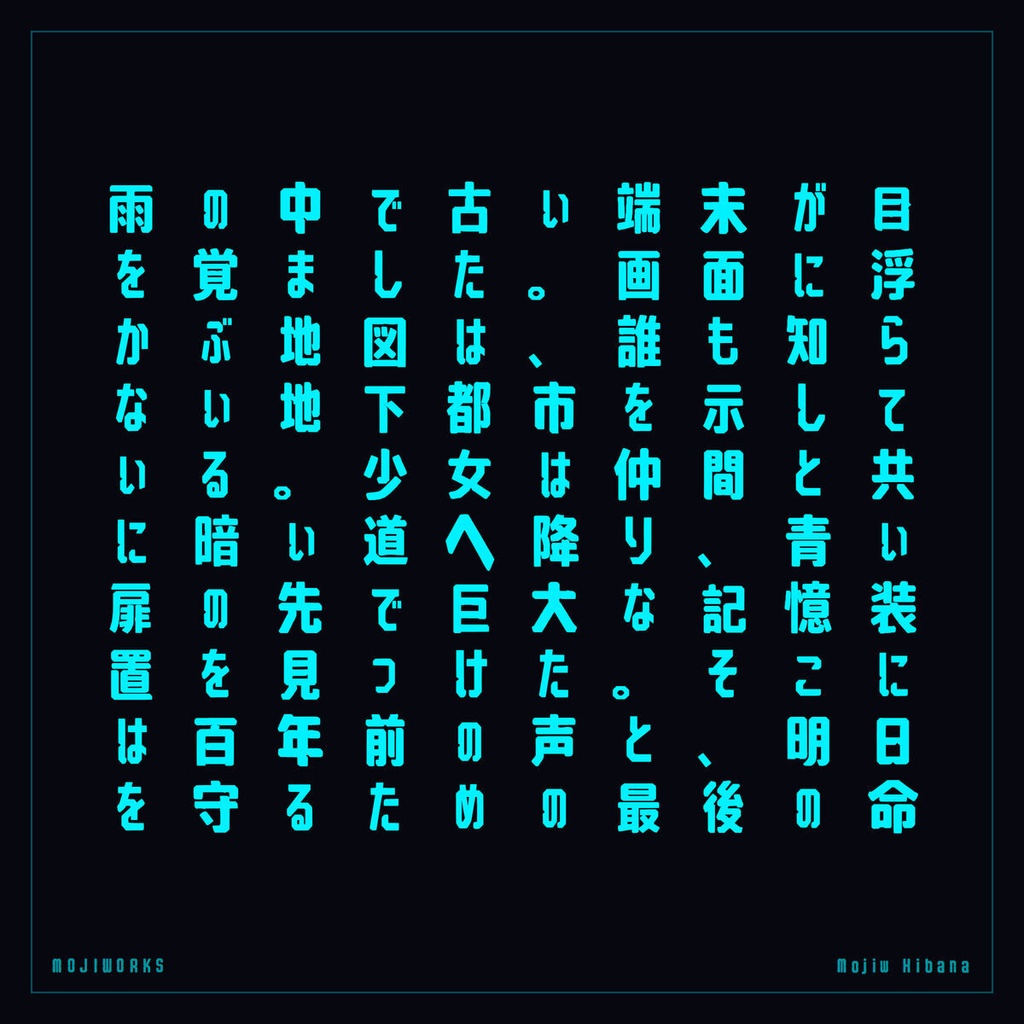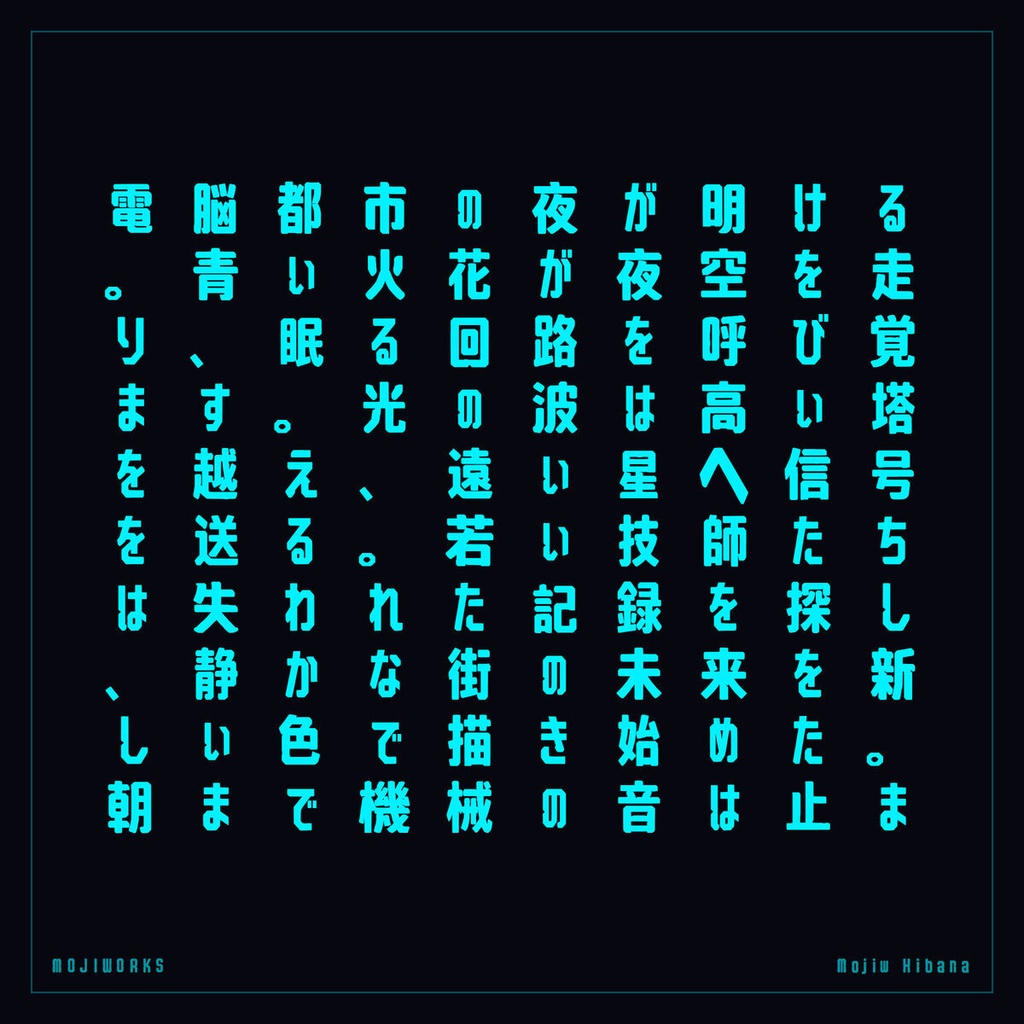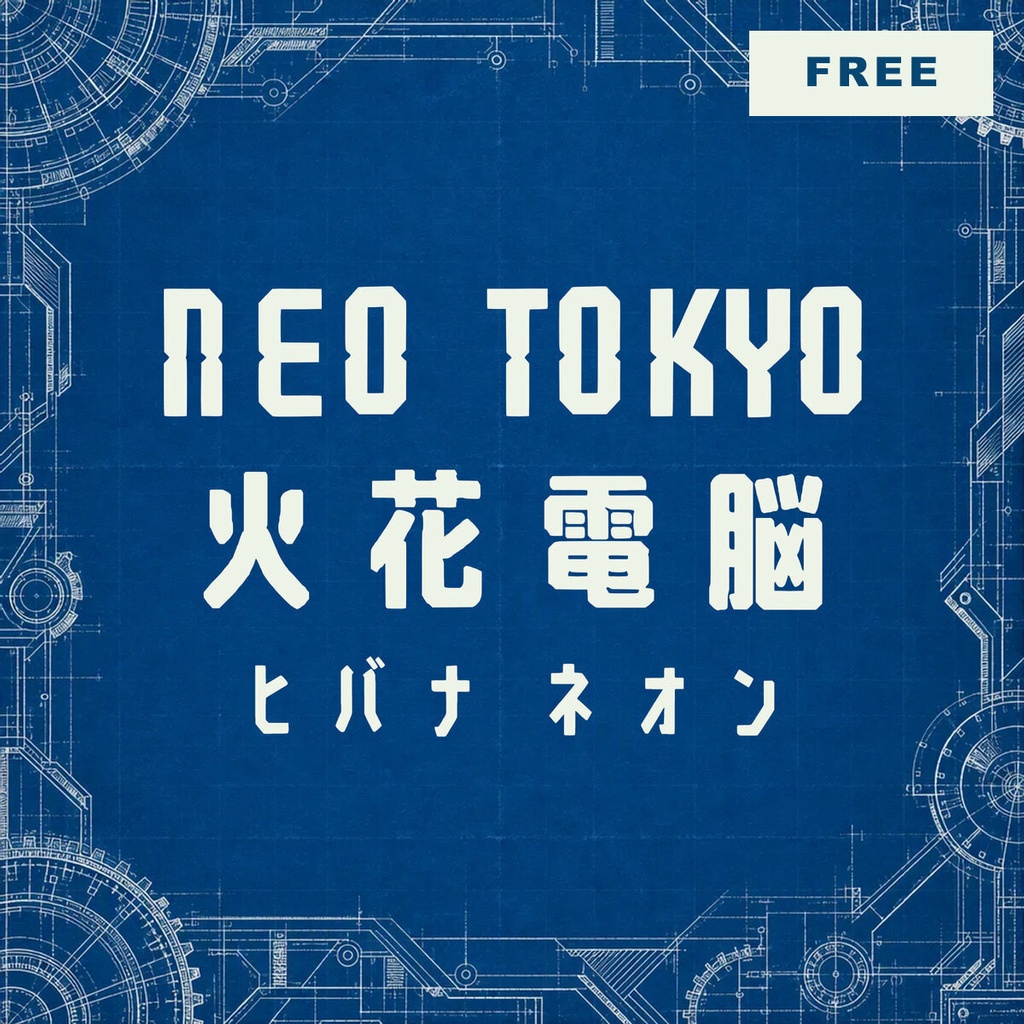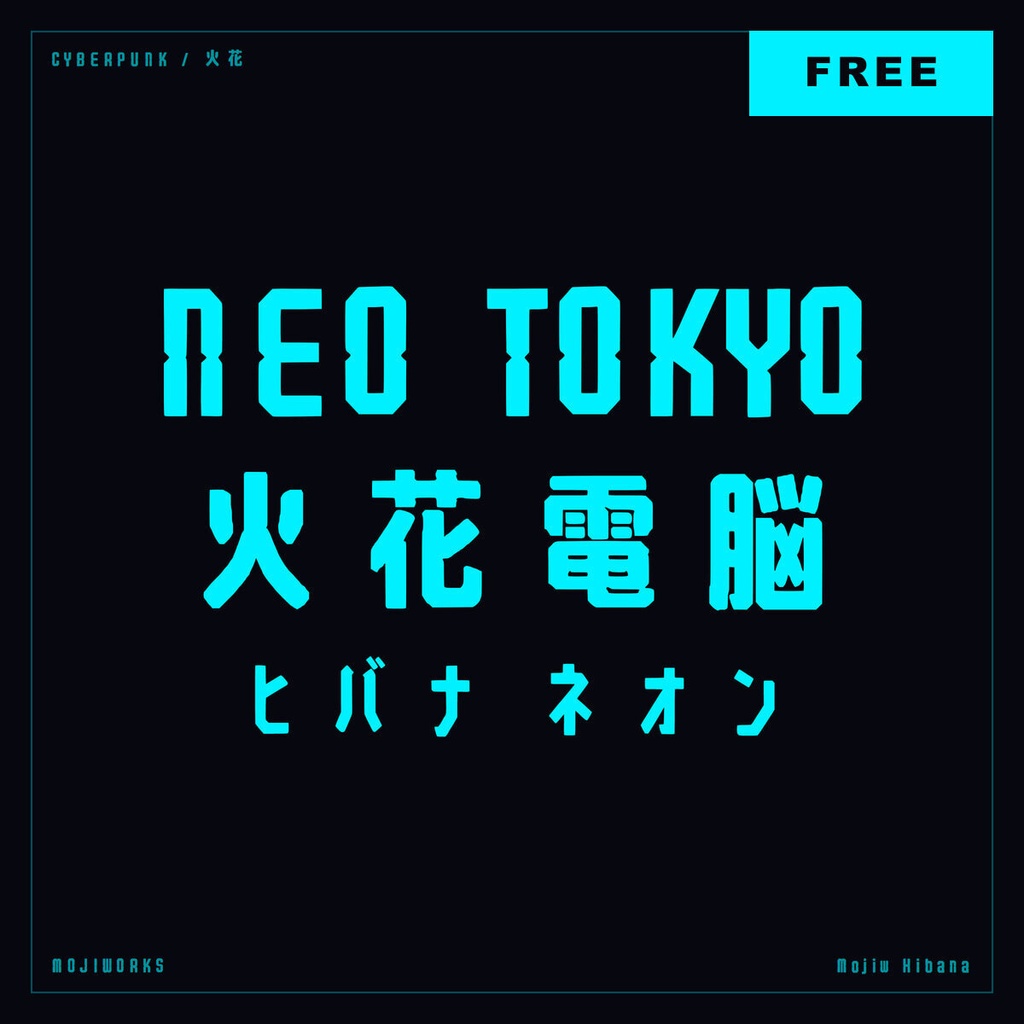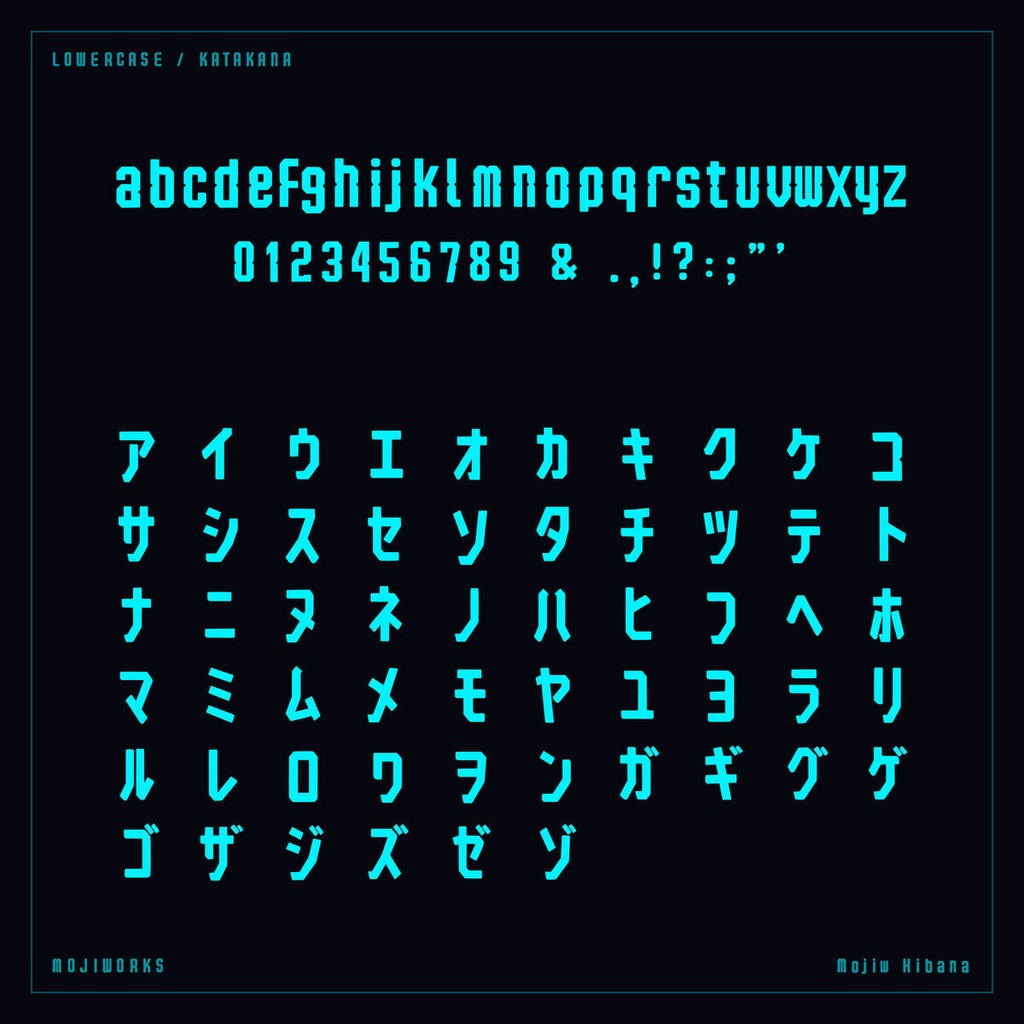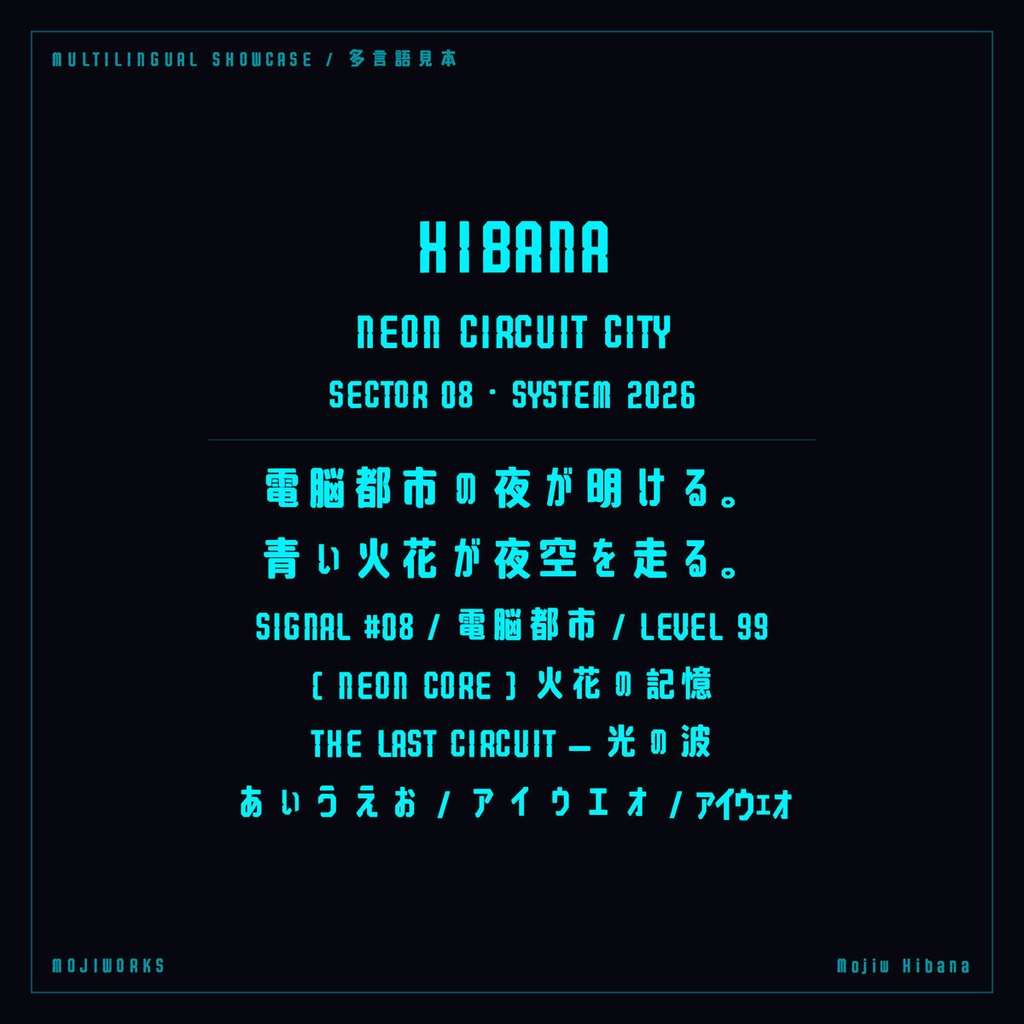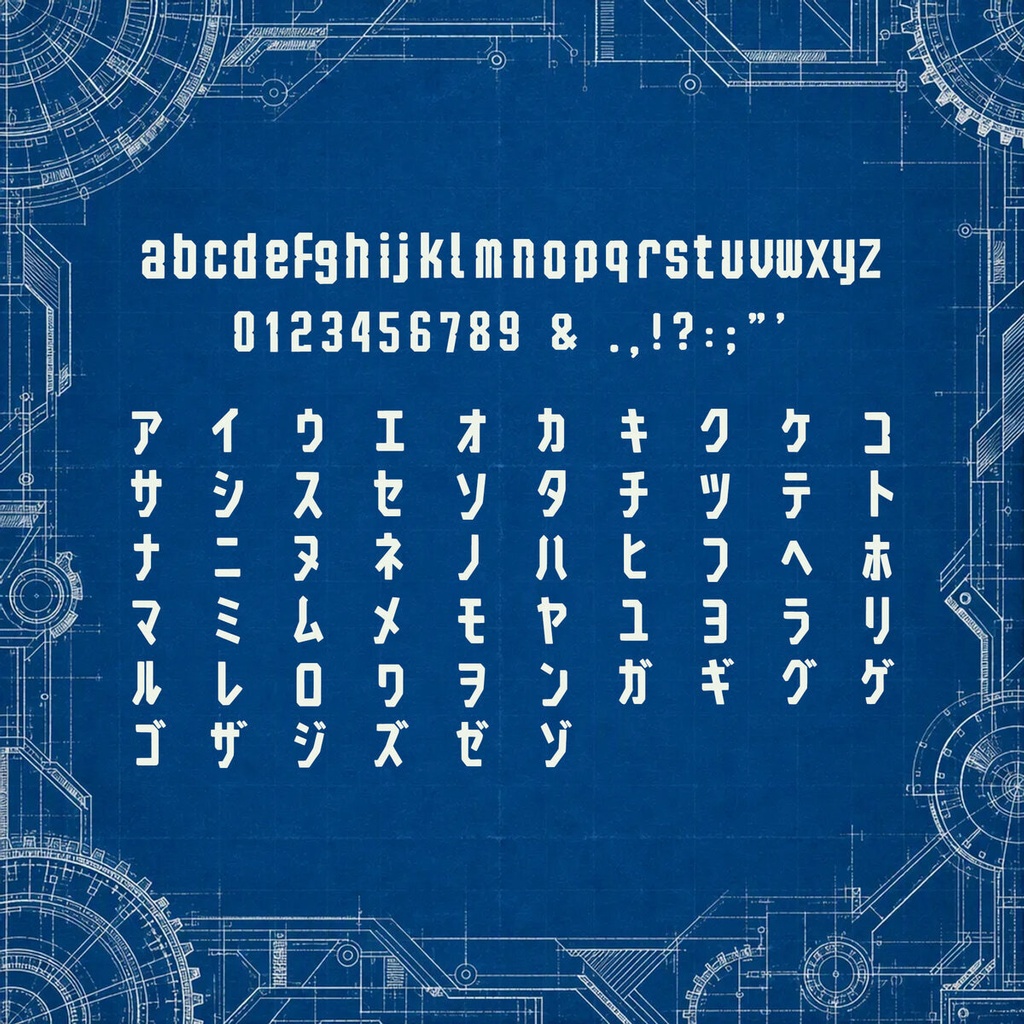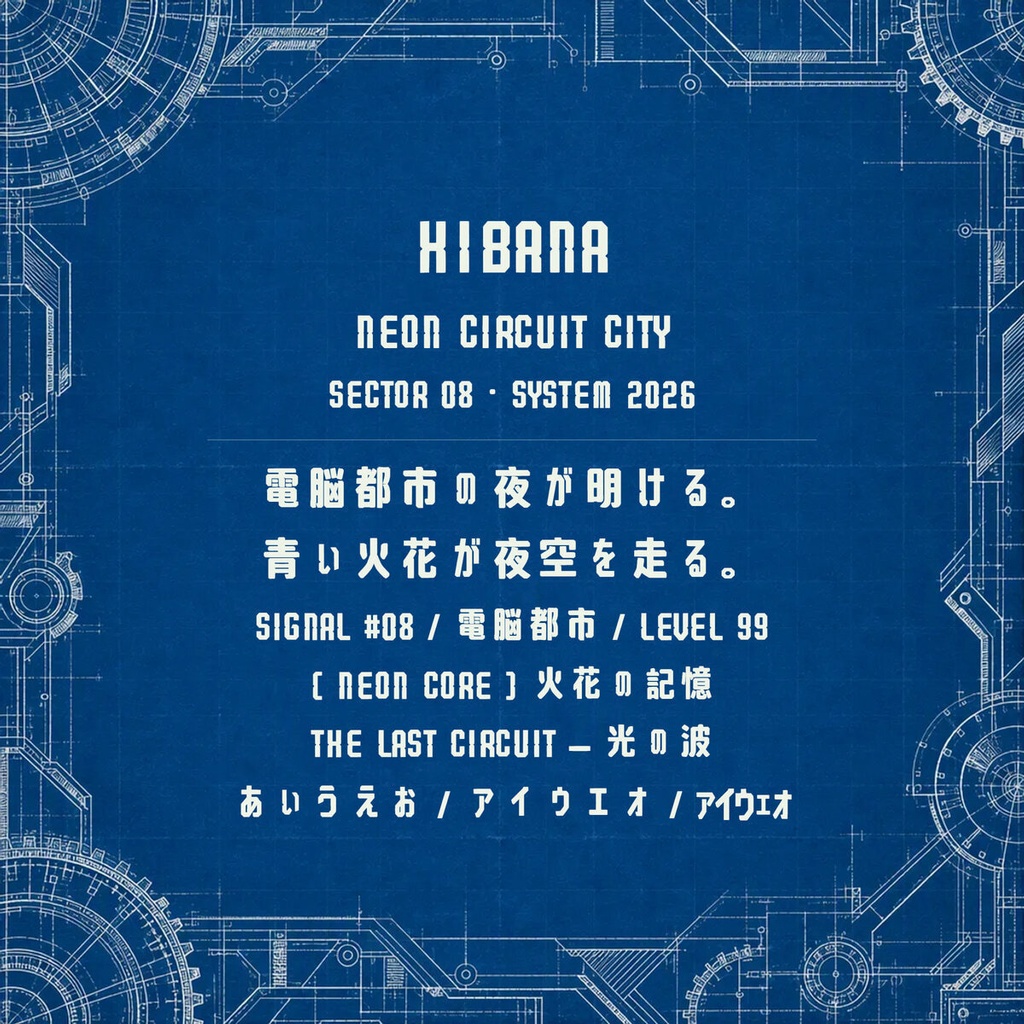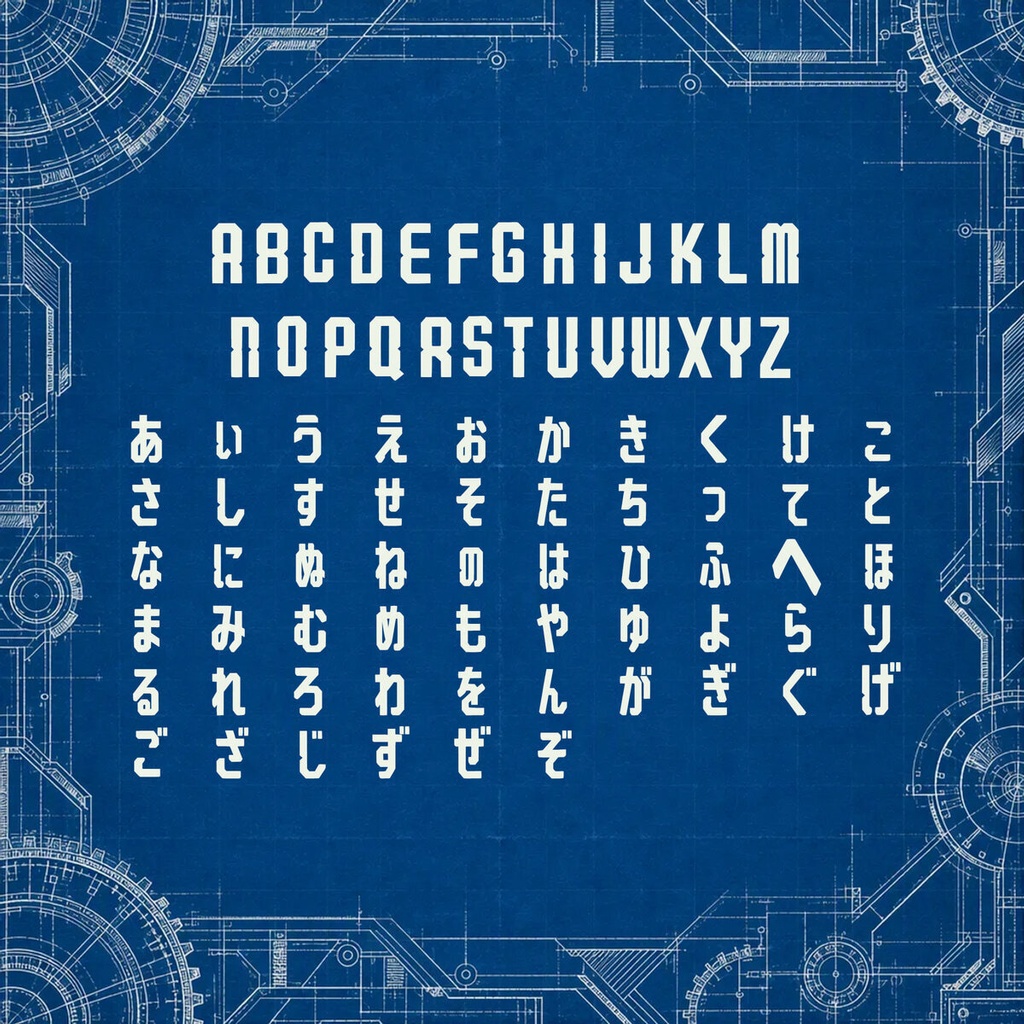
火花 Hibana Standard【フォント】|かな・英数字301文字
ネオンが弾ける、サイバーパンクなディスプレイ書体です。 A cyberpunk display face cut with electric neon energy. 【用途 / Use】 SF / サイバーパンク / 配信OP / EDM MV / ゲームUI For science fiction, cyberpunk, stream openings, EDM videos, and game UI. 【スタンダード版 / Standard】 ラテン文字・ひらがな・カタカナ・記号を全301文字収録しています。漢字・半角カナは収録していません。 Includes 301 characters covering Latin, hiragana, katakana, and punctuation. Kanji and half-width kana are not included. 301文字 / characters 【関連する収録版 / Other Edition】 常用漢字2,136字を含む常用漢字フル版もあります。 The Joyo Complete edition also includes all 2,136 Joyo kanji. ▶ 常用漢字フル版 / Joyo Complete: https://mojiworks.booth.pm/items/8394466 【フォント仕様 / Specification】 バージョン / Version: 1.0.1 形式 / Format: TrueType (.ttf), Web (.woff2) 対応環境 / Platform: Windows, macOS, web browsers 収録字一覧 / Character list: CHARSET.txt 同梱 / Included: font files, README, LICENSE, character list, portfolio PDF, product previews. 【利用規約 / License Summary】 個人・商用利用可。1ライセンスは購入者1名に適用されます。 Personal and commercial use is permitted. One license covers one purchaser. 印刷・動画・ロゴ・グッズ等の静的成果物、および購入者が運営するサイトでの同梱WOFF2の利用が可能です。 Static output such as print, video, logos, and merchandise is permitted. The bundled WOFF2 may be used on a website owned or operated by the purchaser. ゲーム・アプリへの組み込みは、利用者が生のフォントを抽出できない形式に限ります。生のフォントを同梱する場合は別途ライセンスをご相談ください。 Game/app embedding requires protection against extraction of the raw font. Contact us for a separate runtime-embedding license when shipping raw font files. 標準ライセンスは1製品・1サイトあたり年間約100,000ユーザーまで。従業員50名超の組織を含む大規模利用は要相談。 Standard coverage is approximately 100,000 users per product/site/year. Larger use and organizations with more than 50 employees require an extended license. フォント本体の再配布・販売・貸与・変換・グリフ抽出・派生フォント制作・生成AI学習やスタイル参照は禁止です。 Redistribution, resale, lending, conversion, glyph extraction, derivative fonts, and generative-AI training or style reference are prohibited. 完全な利用条件は同梱の LICENSE.txt / LICENSE.jp.txt をご確認ください。 The bundled license files are authoritative; consult them for the complete terms. 【ほかのフォント・カスタム制作 / More Fonts and Custom Work】 フォント一覧、オーダーメイド書体、文字追加、拡張ライセンスのご相談はこちら。 Browse our catalog or contact us for custom typefaces, added characters, and extended licenses. https://mojiworks.booth.pm/